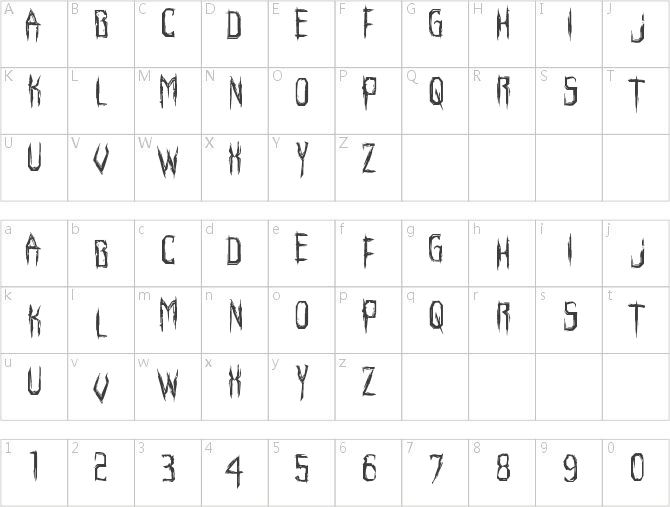
Horroroid Staggered 詳情頁
Horroroid Staggered字體字庫(kù)是一款讓人賞心悅目、百看不厭的英文字體,適合各類廣告和產(chǎn)品包裝設(shè)計(jì)應(yīng)用,字體大小0.13MB,格式為ttf字體,上傳用戶是小李哥/,作者/版權(quán)方為未知